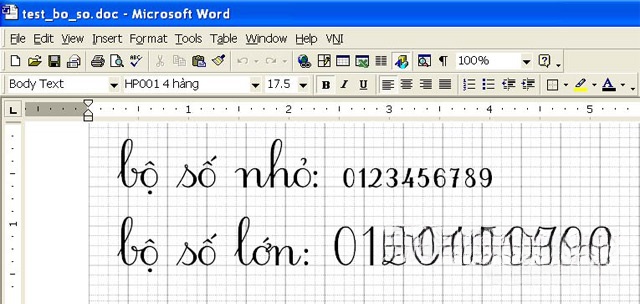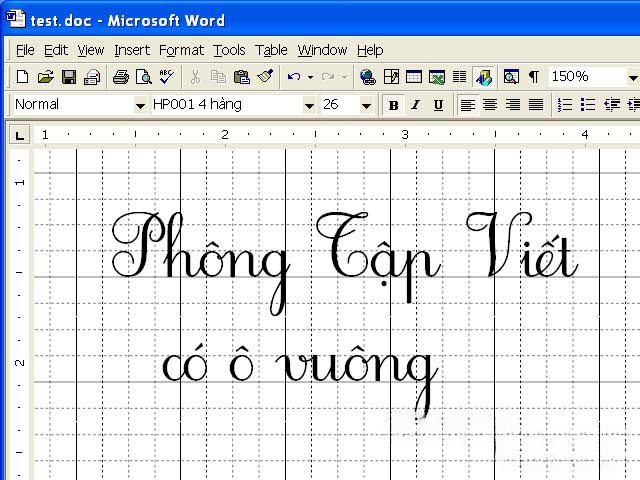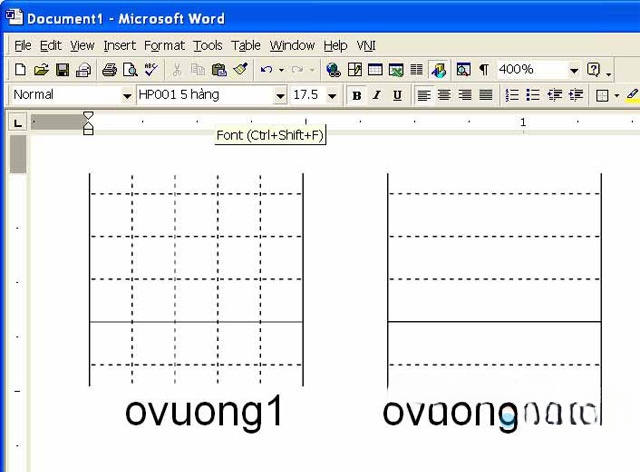
Font chữ tập viết Tiểu học
Font chữ tập viết Tiểu học bao gồm rất nhiều font chữ tập viết dành cho học sinh Tiểu học theo chuẩn của Bộ Giáo dục và Đào tạo. Tất cả chữ cái đều được vẽ bằng
Font chữ tập viết Tiểu học là bộ font tiếng Việt luyện viết cho trẻ em, bộ font tập viết dành để luyện viết cho học sinh lớp 1 nói riêng và tiểu học nói chung. Tải Font chữ tập viết Tiểu học để dễ dàng tạo bộ font chữ mẫu cho các em học sinh ngay tại nhà.
Hiện nay có rất nhiều sách vở tập viết, tuy nhiên bạn vẫn có thể tạo ra những trang chữ viết mẫu cho con em mình luyện viết thông qua Font chữ tập viết Tiểu học. Bộ Font chữ tập viết Tiểu học được áp dụng chặt chẽ các quy định về chữ viết của Bộ Giáo dục và Đạo tạo với từng ly chữ nên mọi người hoàn toàn có thể sử dụng để các em nhỏ luyện chữ viết vào lớp 1.
Font chữ tập viết Tiểu học
Bộ font này, hỗ trợ luyện viết chuẩn nét chữ giúp học sinh hình thành thói quen viết chữ đúng từ những nét cơ bản đầu tiên. Các chữ cái được thiết kế chuẩn tỉ lệ, với độ cao, rộng và khoảng cách giữa các chữ cái hợp lý, kèm theo hướng dẫn nét chữ rõ ràng. Nhờ vậy, học sinh có thể luyện viết từng nét chữ một cách chính xác, rèn kỹ năng nối nét, uốn lượn và viết đúng mẫu chữ chuẩn theo giáo trình tiểu học. Tính năng này không chỉ giúp cải thiện chữ viết mà còn phát triển sự tỉ mỉ, kiên nhẫn và khả năng quan sát chi tiết ở trẻ, tạo nền tảng vững chắc cho việc học tập và viết chữ đẹp trong các năm học tiếp theo.
Cùng với đó, bộ font chữ Tiểu học còn giúp giáo viên và học sinh dễ dàng lựa chọn font chữ theo đúng độ tuổi và trình độ học tập. Bộ font được thiết kế phân theo từng khối lớp từ lớp 1 đến lớp 5, với các nét chữ và kích thước phù hợp cho từng giai đoạn phát triển kỹ năng viết. Nhờ đó, học sinh mới bắt đầu làm quen với chữ cái sẽ có font chữ lớn, rõ nét và dễ theo dõi, trong khi học sinh các lớp cao hơn sẽ luyện tập với font chữ chuẩn, tinh gọn hơn, gần với chữ viết tay thực tế. Tính năng này đảm bảo quá trình luyện viết diễn ra hiệu quả, giúp từng học sinh tiến bộ theo khả năng và nhu cầu riêng, đồng thời hỗ trợ giáo viên soạn bài tập và giáo án chính xác hơn.
Tính năng chính của bộ font chữ tập viết Tiểu học
- Chữ viết chuẩn: Đây là tính năng quan trọng nhất. Bộ font cung cấp các kiểu chữ viết tay và chữ in theo đúng quy định về cỡ chữ, độ dốc, và khoảng cách, giúp học sinh làm quen và luyện tập viết chữ đẹp, đúng quy cách ngay từ những năm đầu tiên.
- Đa dạng kiểu chữ: Font tập viết thường bao gồm nhiều phiên bản như chữ in thường, chữ in hoa, chữ viết thường và chữ số, giúp học sinh học và thực hành toàn diện.
- Nét đứt: Nhiều bộ font tập viết có phiên bản nét đứt, cho phép giáo viên và phụ huynh tạo ra các bài tập tô chữ. Tính năng này giúp các em học sinh dễ dàng làm quen với hình dáng của từng chữ cái, từ đó hình thành thói quen viết đúng nét, đúng thứ tự.
- Kẻ ô ly: Một số font chữ đặc biệt còn tích hợp sẵn kẻ ô ly, mô phỏng giống hệt vở tập viết của học sinh. Điều này rất hữu ích cho việc tạo tài liệu luyện tập và đảm bảo các chữ được viết đúng vị trí, đúng tỉ lệ trên dòng kẻ.
Bộ font chữ tập viết này có 2 loại: 4 hàng và 5 hàng:
Loại 4 hàng giống tập học sinh 4 ô ly, nhưng không thể hiện được các ký tự Ô Ắ ... Tất cả có 4 file font bao gồm:
Font chữ tập viết Tiểu học
Bộ font chữ luyện viết